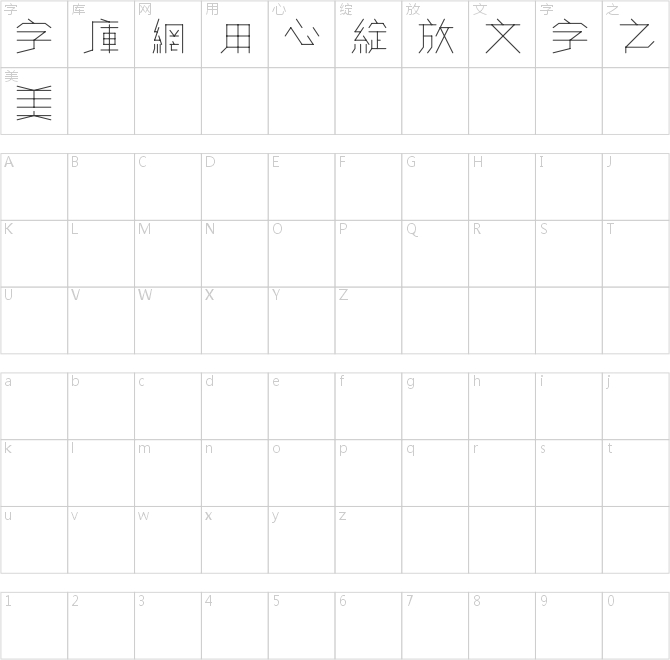
黃令東細線體
黃令東細線體是一款十分特別的字體,這款字體是用程序自動生成,用遞歸根式包裝語言(RRPL)進行編寫。在RRPL中,每個漢字被描述為數字、符號和對其他字符的引用的短字符串。它的語法靈感來自標記語言,如乳膠,以及傳統的用于書法練習的“米”網格。
目前黃令東細線體使用5000+的繁體漢字和詞根,其字形由默認解析器生成。如有興趣,可以點擊這里去觀看字體生成的演示程序。由于是程序自動生成的字體,所以難免會有錯別字,大家使用時請檢查清楚。
值得注意的是,這款字體是繁體的詞根,輸入簡體字的話會直接映射成繁體字形。比如說你輸入“漢”字,會被成繁體的“漢”字。